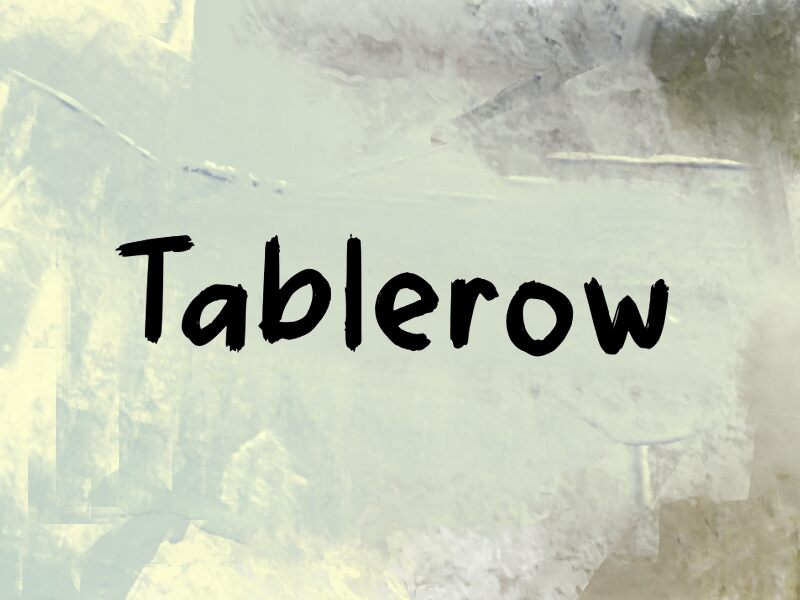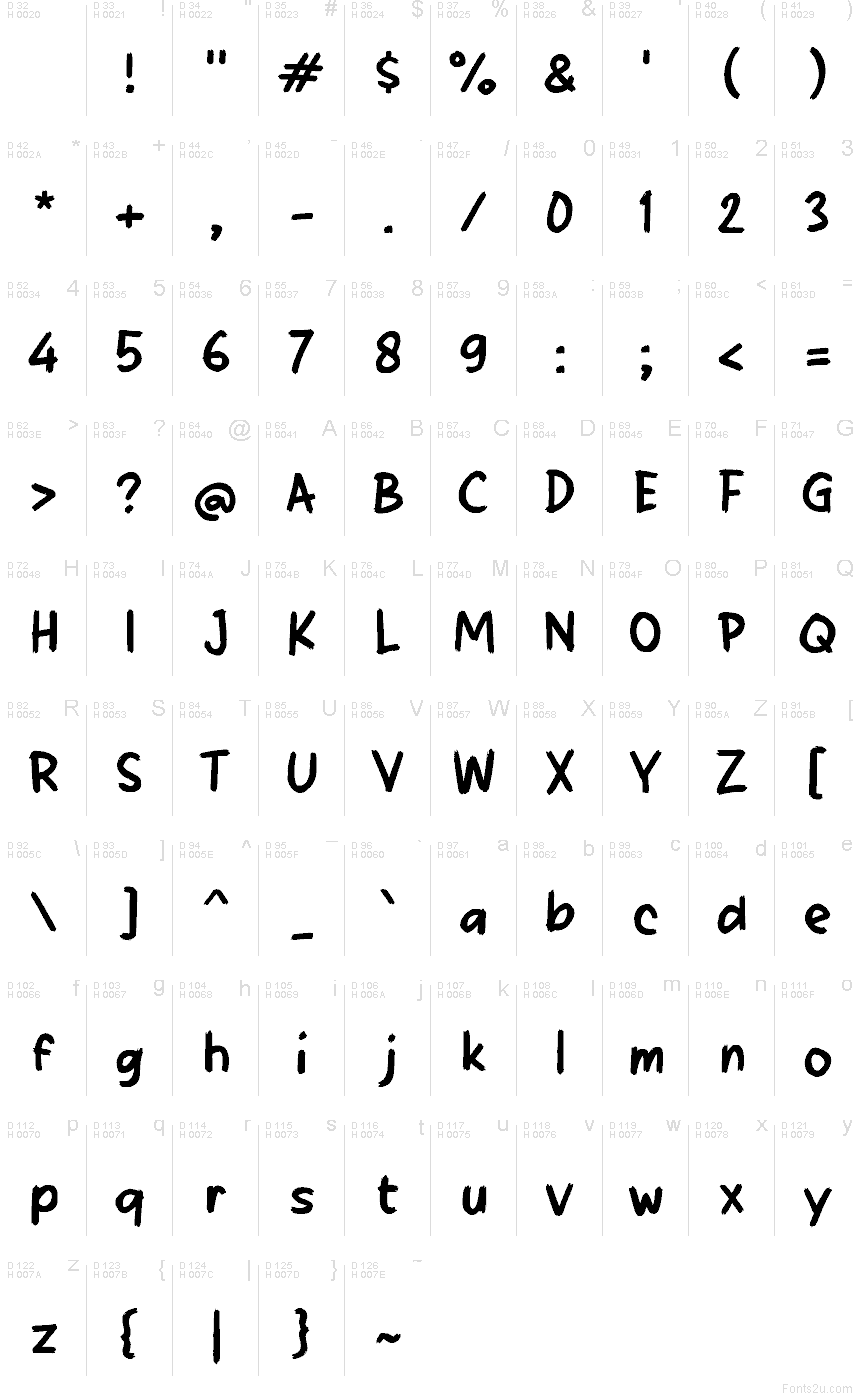
Tablerow od Wep je bezplatné písmo typu brush, definované širokými, suchými tahy, které na písmenech zanechávají roztřepené okraje a strohé konce. Tato drsná, malovaná textura mu dodává autentický ruční nádech, díky čemuž působí spíše jako rychlá ruční malba než jako uhlazená kaligrafie.
Skvěle se hodí na grafiku křídových tabulí v restauracích, jídelní lístky food trucků, plakáty na akce, etikety produktů nebo záhlaví na sociálních sítích. Mírně nepravidelná textura tahů dodává krátkým řádkům živost a neformálnost, takže Tablerow ideálně podtrhne ležérní branding nebo nadpisy, aniž by sklouzlo k příliš upjatému vzhledu.
Tablerow
Prezentace a vizuální ukázka písma Tablerow